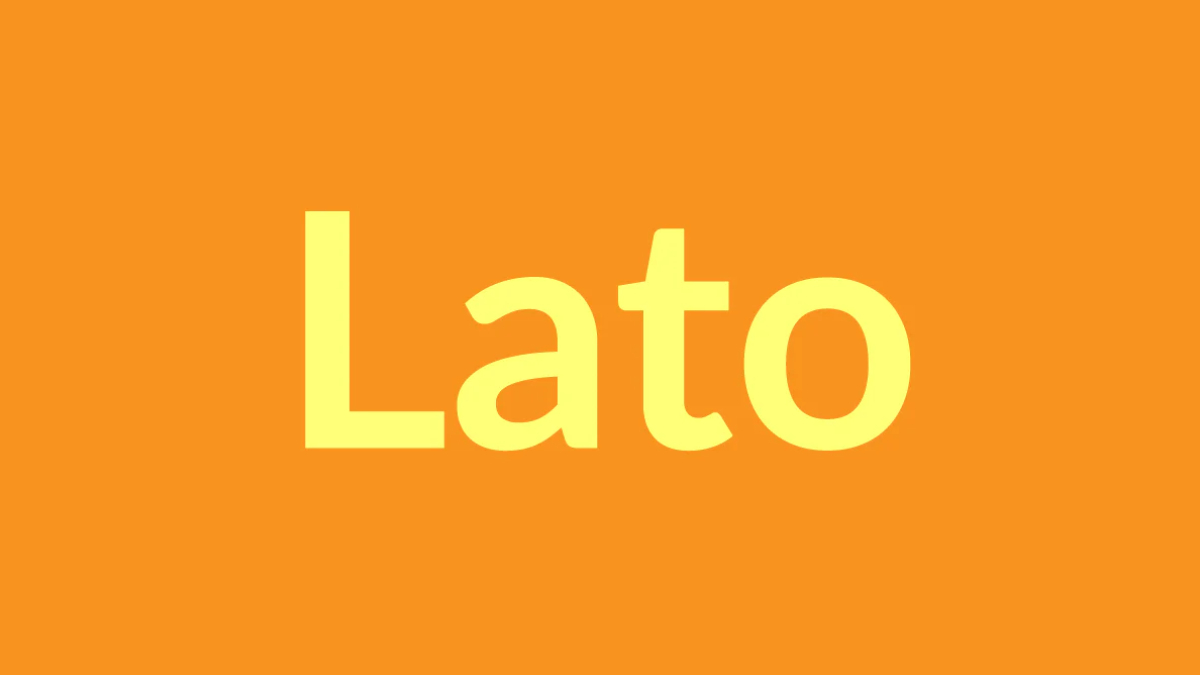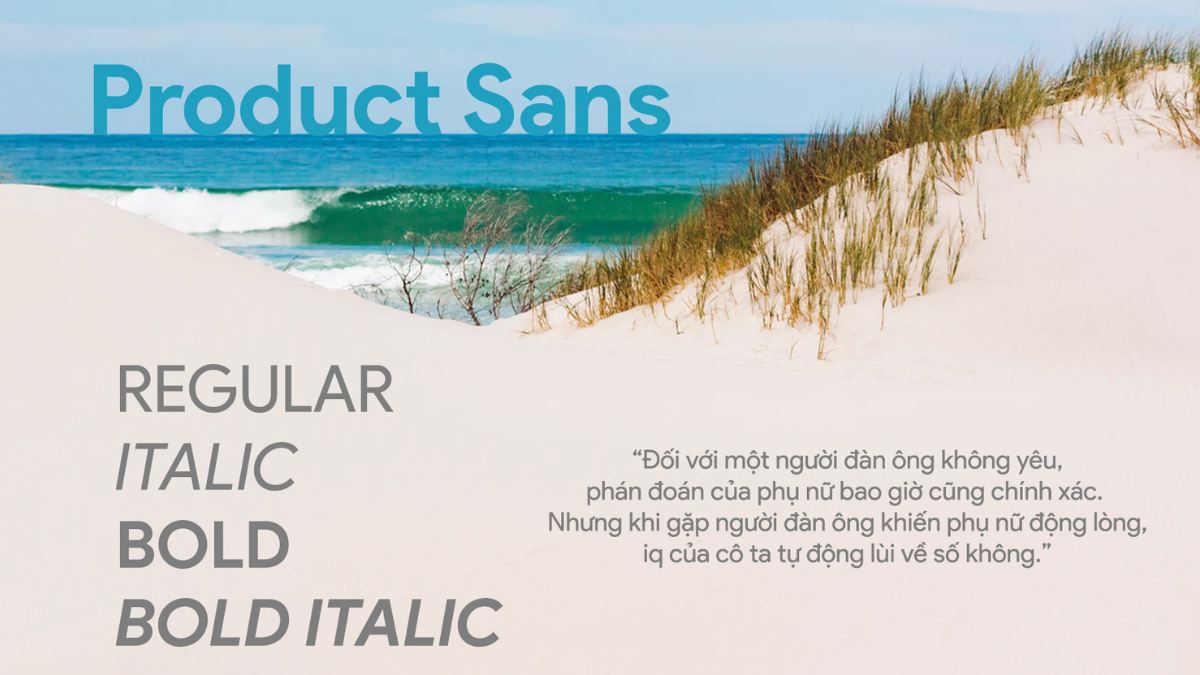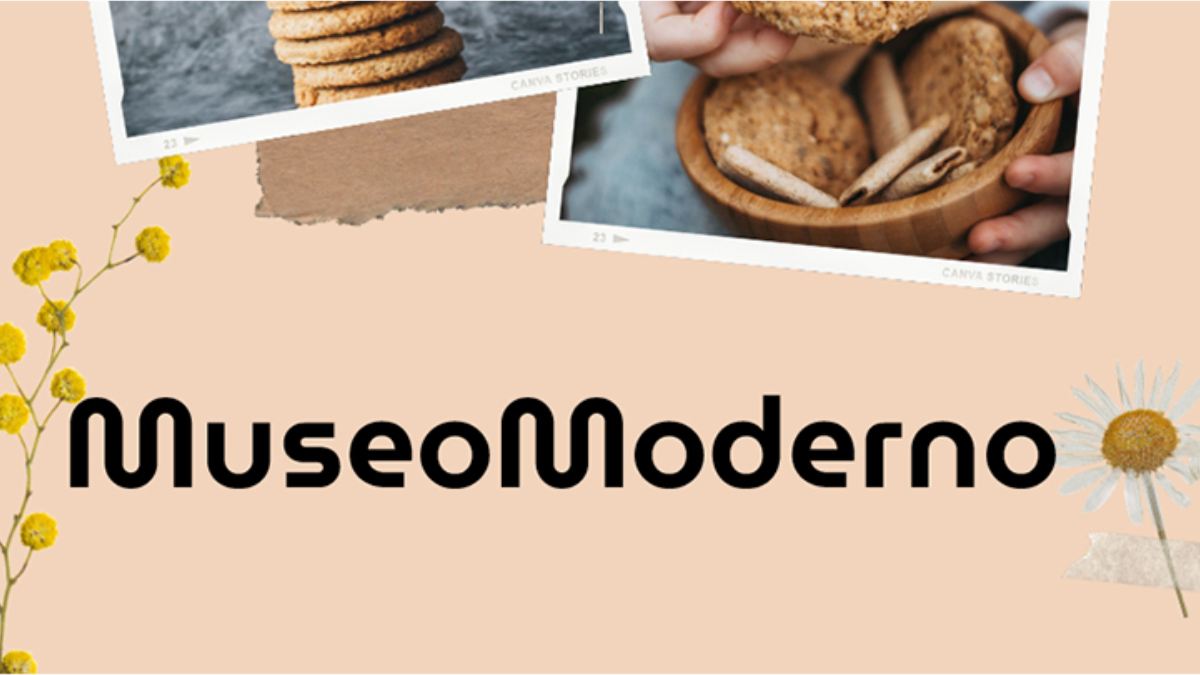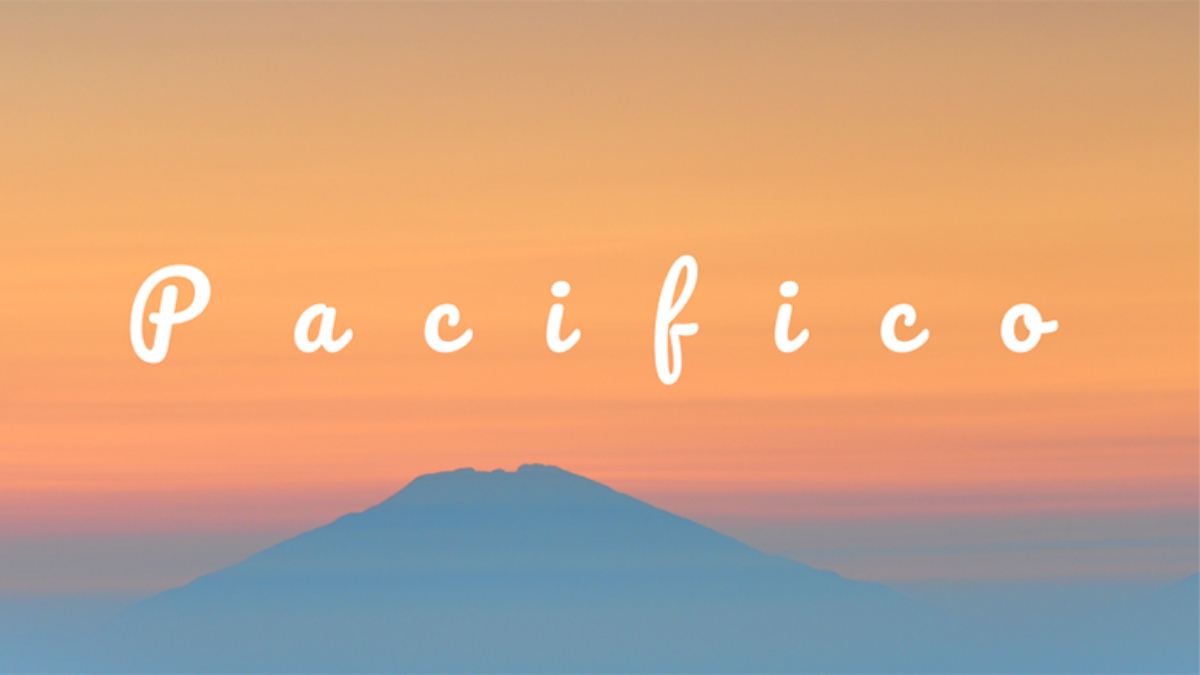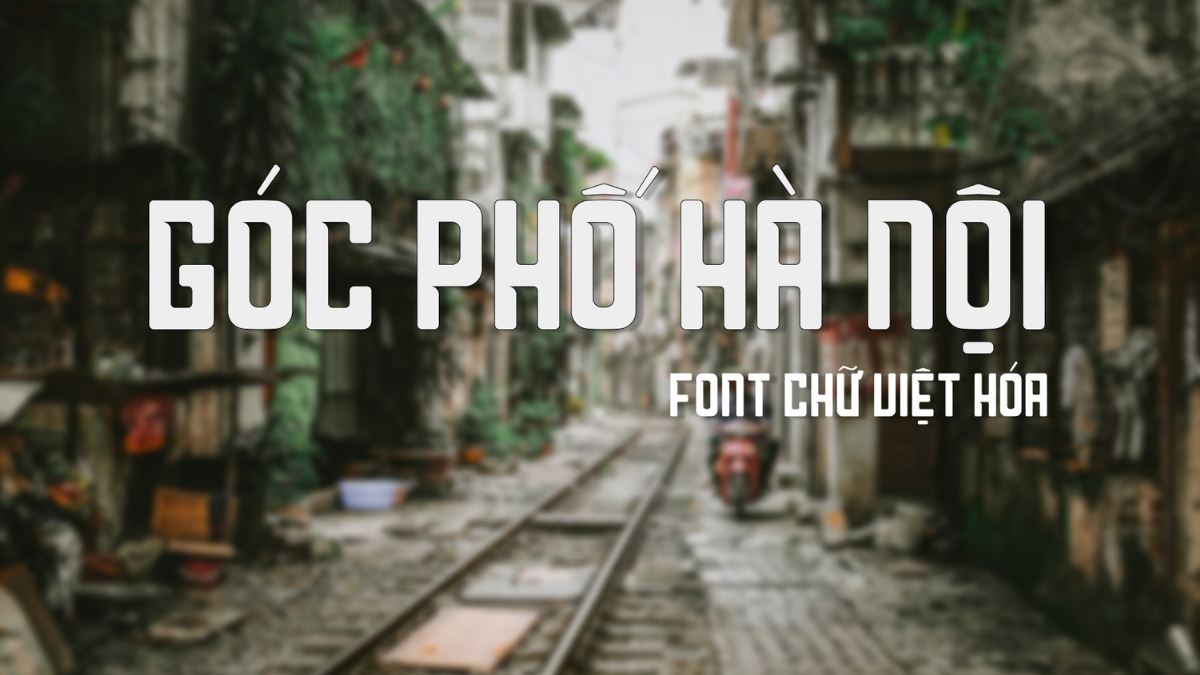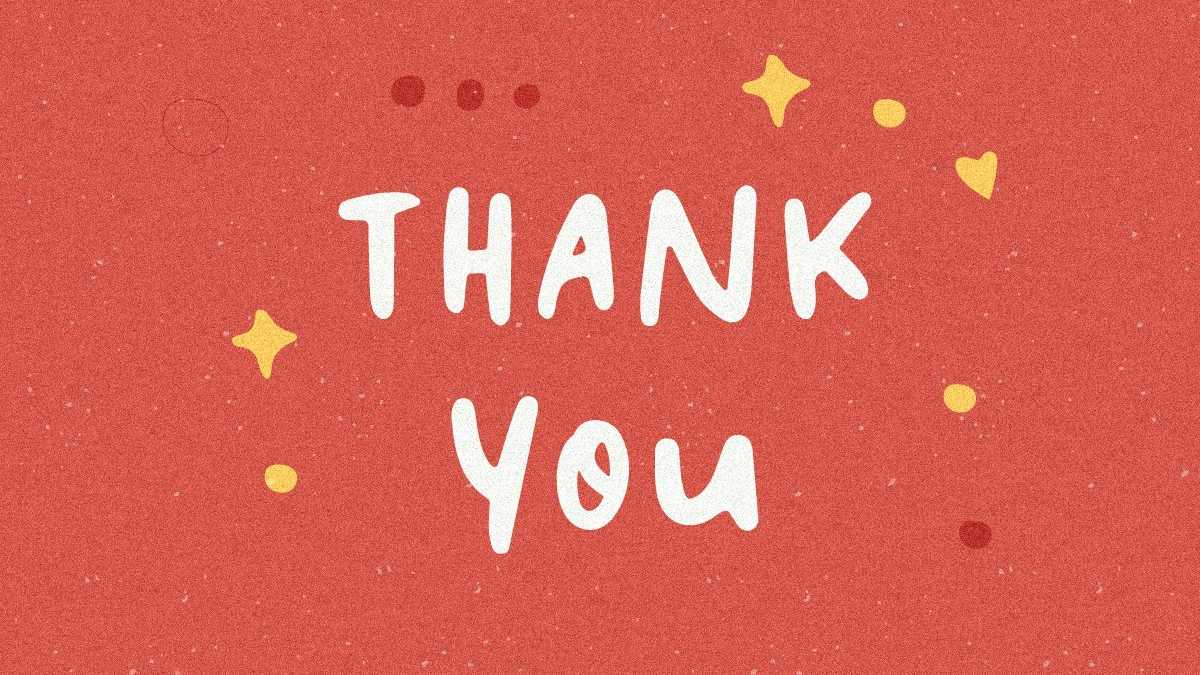
Top Font Chữ Đẹp Cho Thiết Kế: Lato, SVN-Product Sans và Nhiều Hơn Nữa
Việc chọn lựa font chữ phù hợp đóng vai trò quan trọng trong thiết kế, ảnh hưởng đến cả tính thẩm mỹ và khả năng truyền tải thông tin. Bài viết này sẽ giới thiệu đến bạn đọc những font chữ đẹp, phổ biến và được ưa chuộng nhất hiện nay, giúp bạn tạo ra những thiết kế ấn tượng và chuyên nghiệp.
Font chữ là yếu tố quan trọng trong thiết kế, giúp truyền tải thông điệp hiệu quả và tạo nên tính thẩm mỹ cho sản phẩm. Vậy tại sao nên sử dụng font chữ đẹp cho thiết kế? Một font chữ đẹp và phù hợp sẽ giúp nội dung trở nên thu hút, dễ đọc, dễ tiếp thu, đồng thời làm nổi bật nội dung và tạo nên sự hài hòa cho tổng thể thiết kế. Hơn nữa, việc sử dụng font chữ chuyên nghiệp cũng góp phần xây dựng hình ảnh đáng tin cậy và thể hiện sự sáng tạo của người thiết kế. Cuối cùng, một font chữ dễ đọc sẽ giảm thiểu tình trạng mỏi mắt, giúp người xem tiếp thu thông tin nhanh chóng và hiệu quả hơn.
Tại sao nên sử dụng các font chữ đẹp cho thiết kế
Những Font Chữ Đẹp Được Ưa Chuộng Trong Thiết Kế
Dưới đây là một số font chữ đẹp, đang được ưa chuộng trong lĩnh vực thiết kế, từ thiết kế web, in ấn, quảng cáo đến thiết kế đồ họa. Mỗi font chữ đều mang một nét đặc trưng riêng, đáp ứng đa dạng phong cách và nhu cầu của người dùng.
Font Lato
Ra mắt năm 2010 bởi nhà thiết kế Łukasz Dziedzic, Lato là một font chữ Sans-serif với đường nét mềm mại, thẳng và các góc bo tròn nhẹ. Tính linh hoạt của Lato cho phép nó được sử dụng trong nhiều mục đích khác nhau, từ in ấn, quảng cáo, báo chí đến thiết kế web và tài liệu văn bản.
Font Lato - Font chữ đẹpFont Lato – Font chữ đẹp
Font SVN-Product Sans
Được phát triển bởi Google, SVN-Product Sans mang phong cách đơn giản nhưng hiện đại và thẩm mỹ. Font chữ này thường xuất hiện trên tờ rơi, bìa album, thiết kế thời trang, ứng dụng và trang web nhờ khả năng tương thích cao trên nhiều nền tảng.
Font SVN-Product Sans chữ đẹp
Font Museo Moderno
Phát hành năm 2015 bởi Jos Buivenga, Museo Moderno là một lựa chọn phổ biến cho thiết kế logo, bản in, trang web và đồ họa. Các đường viền chuyên nghiệp của font chữ này tạo ấn tượng mạnh mẽ và thu hút sự chú ý của người xem.
Font Museo Moderno
Font Pacifico
Pacifico là một font chữ cursive (thư pháp) được thiết kế bởi Vernon Adams. Với phong cách vui nhộn và đáng yêu, Pacifico thường được sử dụng trong các thiết kế liên quan đến chủ đề biển, lướt sóng hoặc Hawaii, tạo cảm giác thân thiện và tự nhiên cho poster, bìa quảng cáo.
Font Pacifico
Font iCielBC Downtown
iCielBC Downtown là một font chữ phổ biến trong nhiều lĩnh vực. Các đường nét được việt hóa với độ dày khác nhau, tạo hiệu ứng cân bằng và tương phản giữa chữ viết và khoảng trắng.
Font iCielBC Downtown
Font SVN-TheUntold Story
SVN-TheUntold Story được thiết kế với các ký tự thiên về hướng chân dung, mang lại cảm giác thân thiện và dễ đọc. Sử dụng đồ họa vector, font chữ này đảm bảo độ sắc nét và chất lượng cao trong từng chi tiết.
Font SVN-TheUntold Story